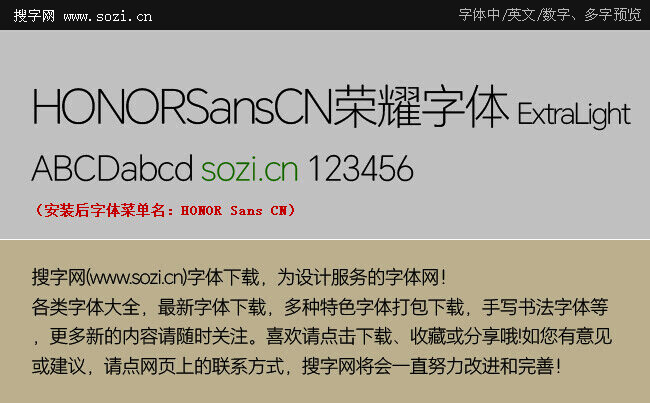
HONORSansCN荣耀字体ExtraLight
搜字网给大家提供一款HONORSansCN荣耀字体ExtraLight中文字体下载,荣耀字体HONOR Sans是由荣耀MagicOS联手方正带来的一套全新的免费可商用中文字体,包含了 9 种字重,HONOR Sans拥有简洁生动的笔划以及平滑优美的曲线,相比标准的黑体则在笔画的曲率、结构布局上进行了优化,很好地提升了可读性以及文字辨识度,让排版更加舒服,看起来也更加优雅,能有效降低长时间阅读时对视觉造成的疲劳。 适用于标题设计、海报设计、书籍排版以及网页设计等应用。